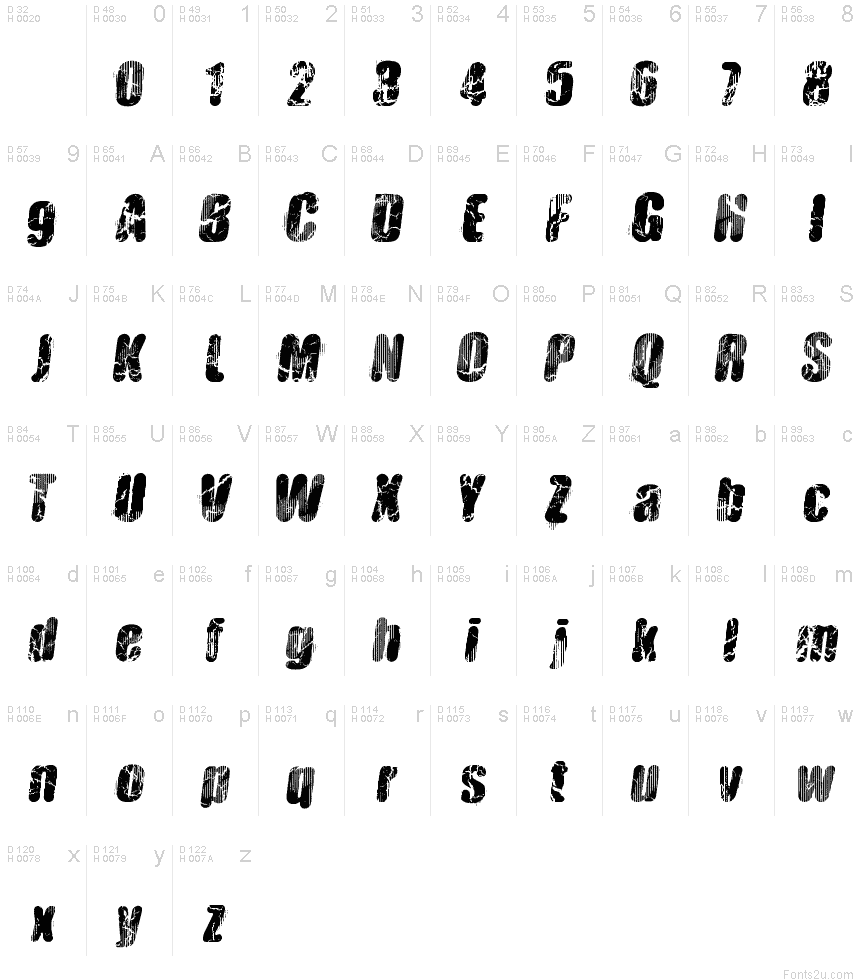
Vtks Hardness, bezpłatny grunge'owy krój displayowy autorstwa Douglasa Vitkauskasa, stawia na surowy wygląd w stylu pieczątki, z masywnymi literami pokrytymi pęknięciami, wyszczerbieniami i śladami pionowego zużycia. Kształty pozostają duże i wyraziste, a powtarzające się uszkodzenia nadają krojowi żywy, „zmęczony” rytm – sprawia on wrażenie nadruku na zniszczonej ścianie, a nie rysunku na czystej kartce.
Idealnie nadaje się do plakatów, okładek płyt, zinów, nagłówków, ulotek i wyrazistych znaków graficznych, wszędzie tam, gdzie darmowy font ma wnieść teksturę bez konieczności dodawania kolejnych efektów. Używaj go zwłaszcza w krótkich tytułach i przyciągających wzrok hasłach – popękane powierzchnie robią całą robotę, zanim jeszcze dodasz jakiekolwiek elementy graficzne.
Prezentacja i próbka wizualna czcionki Vtks Hardness